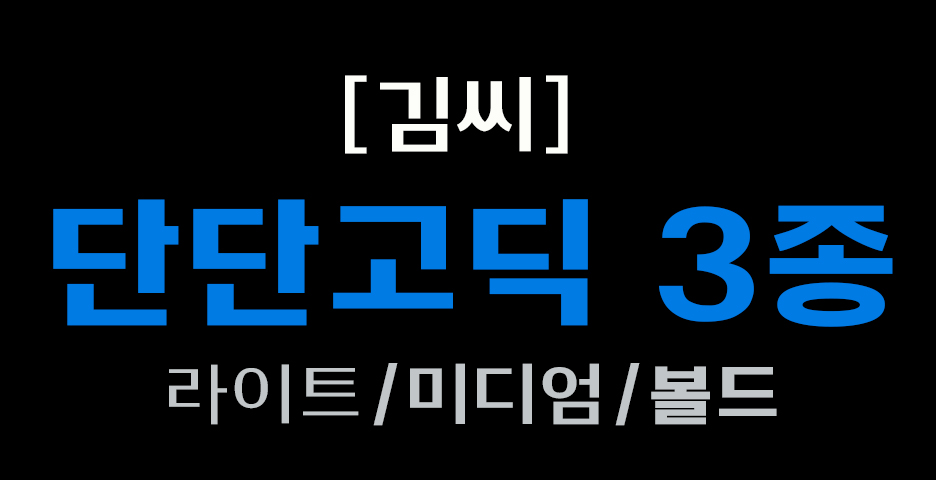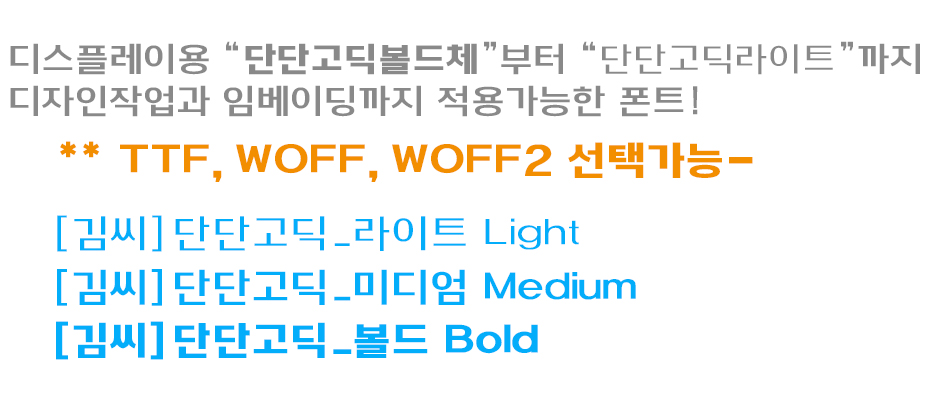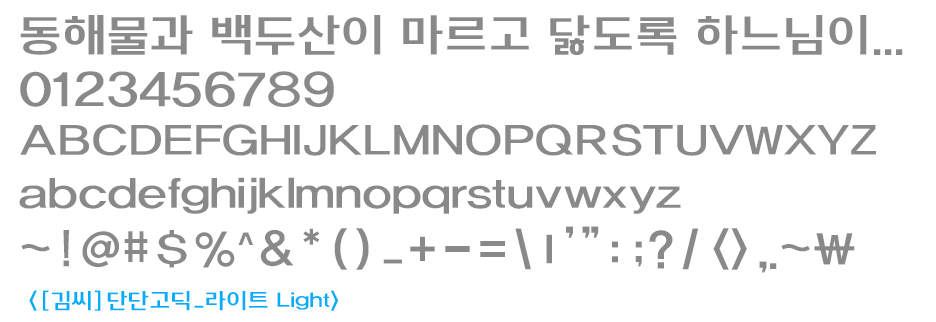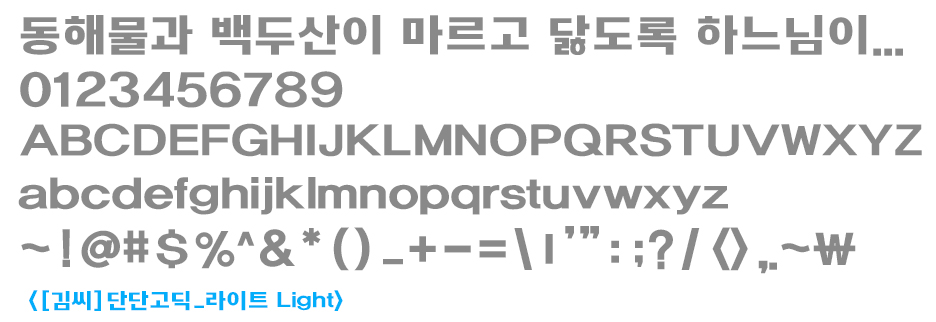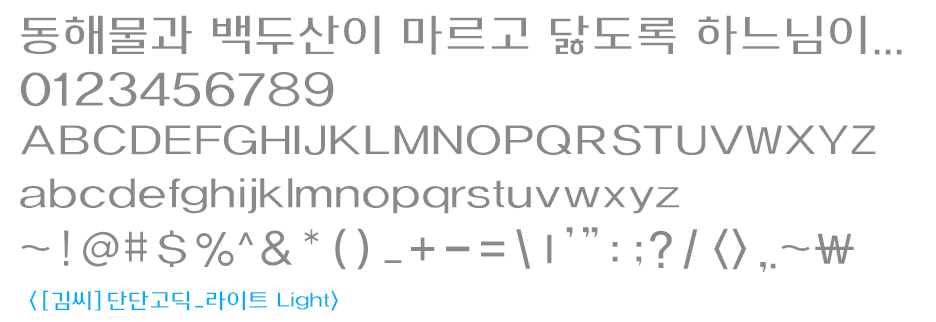
● ● 특장점
1. 강한 시인성
• 전통적인 인쇄용 한글의 글꼴을 기본으로 직선적이며, 깔끔한 획의 처리로 폰트의 시인성이 뛰어남.
2 한글·영문 통일감 우수
• 한글과 영문의 굵기와 비례가 잘 맞아 혼용 문장에서 이질감이 적습니다.
3. 현대적이고 강렬한 인상
• 직선 중심의 고딕 스타일로 세련되고 역동적인 이미지를 전달합니다.
4. 대형 디스플레이 환경에 최적화
• 포스터, 광고, 썸네일, 배너 등 큰 크기에서 뛰어난 존재감을 보여줍니다.
• 유튜브 썸네일이나 광고 카피에서 특히 효과적입니다.
5. 균형 잡힌 자폭과 안정적인 조형
• 여러 줄 조판 시 덩어리감이 좋고 화면 구성이 안정적으로 보입니다.
6. 강한 브랜드 아이덴티티 형성 가능
• 독특한 굵기와 묵직한 인상 덕분에 브랜드 로고 및 슬로건 제작에 유리합니다.
• 한 번 보면 기억하기 쉬운 시각적 개성을 제공합니다.
[김씨]단단고딕체